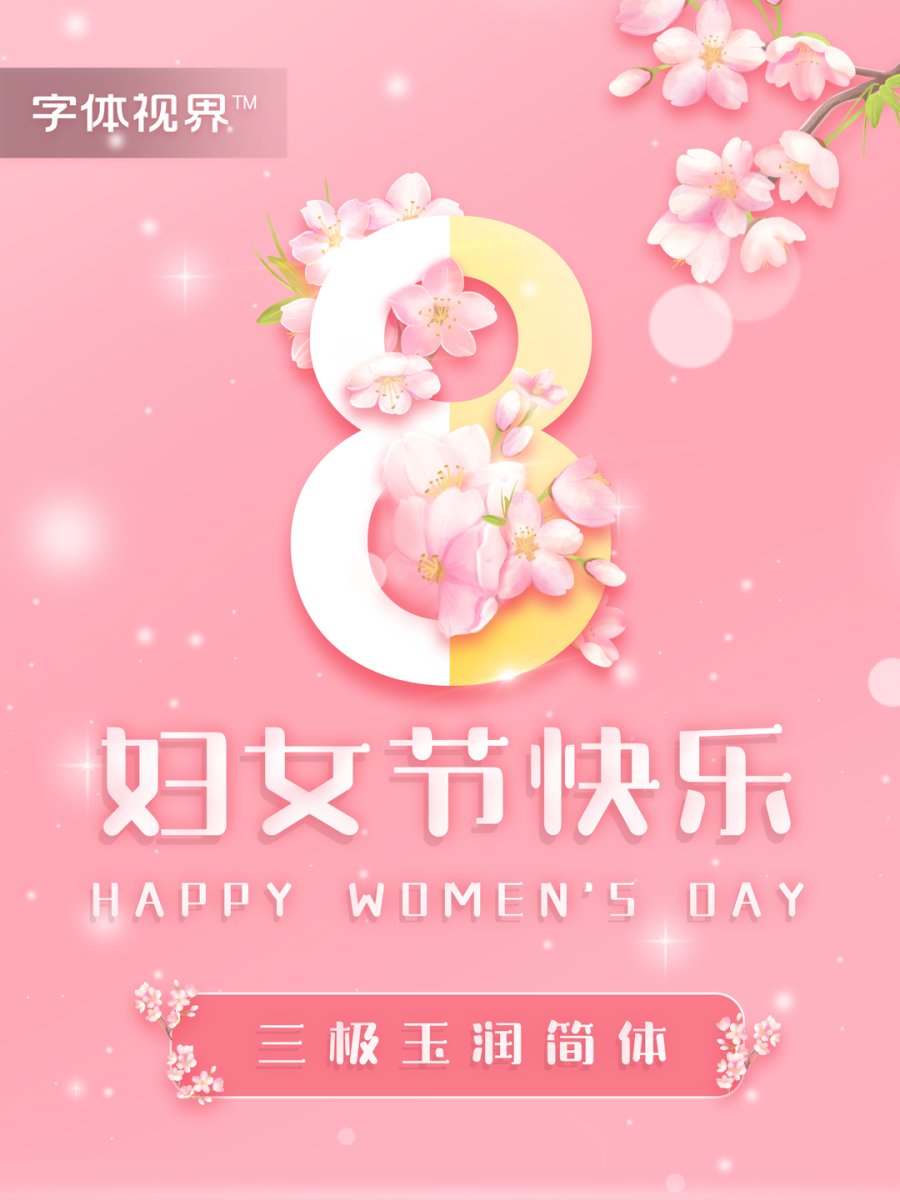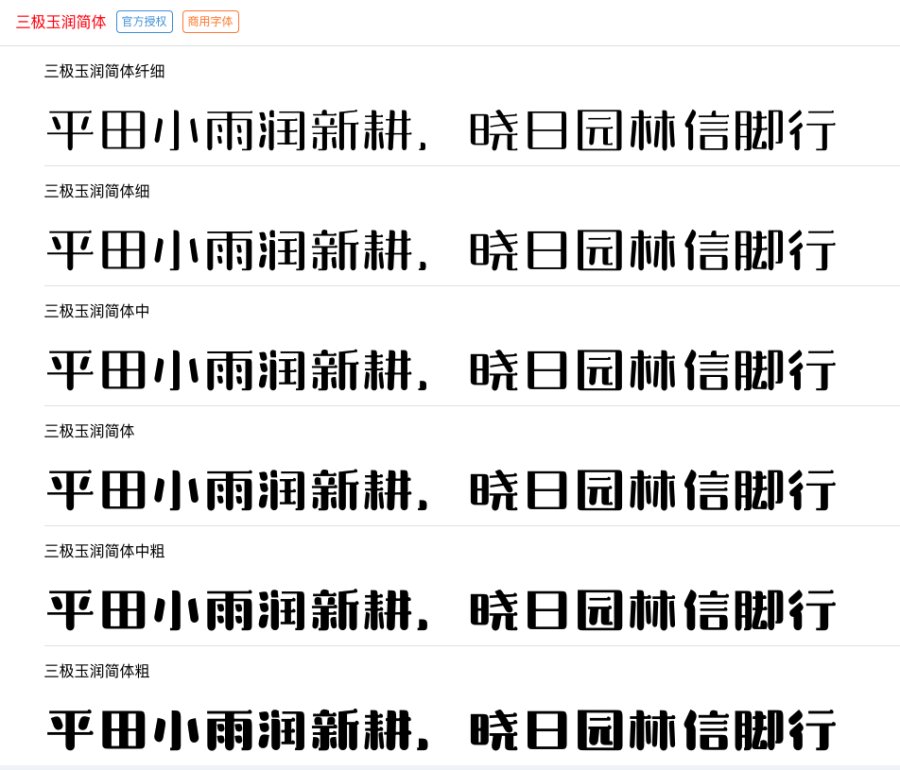
一年一度的三八妇女节即将到来,在这个特殊的日子里,怎么能缺少来自字体视界的字体仪式感呢?今天小字给大家带来的是一款三极字库出品的创意圆润字体——三极玉润简体。
这款字体横细竖粗,横是细的,不会显整体厚重感,右边加了个小圆包,凸显可爱俏皮。竖是粗的,上面左50往下120做一个半圆的设计,底下也做了半圆,凸显出了整个字体的圆嘟嘟的宗旨,这款字的宝盖头也是圆润饱满的和点相呼应,整体风格圆润但是不厚重。